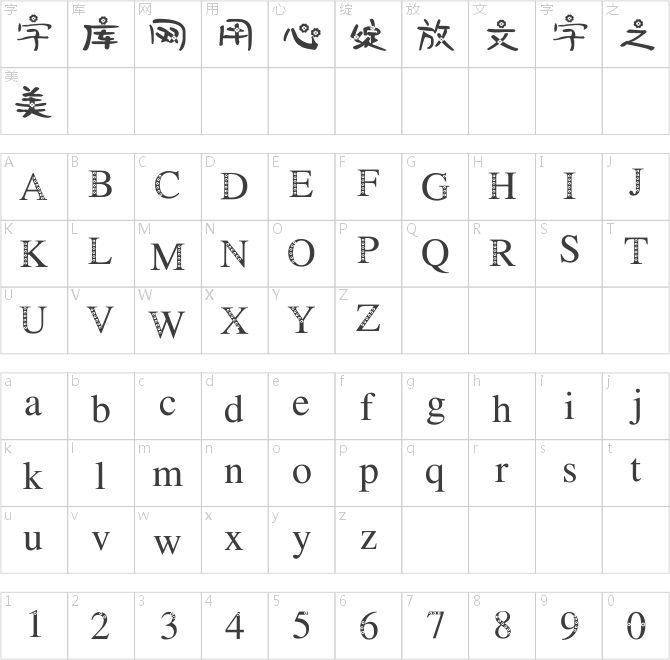
南構(gòu)花韻
南構(gòu)字庫(kù)
南構(gòu)花韻字體字庫(kù)是一款讓人賞心悅目、百看不厭的中文字體,適合各類(lèi)廣告和產(chǎn)品包裝設(shè)計(jì)應(yīng)用,字體大小3.69MB,格式為ttf字體,上傳用戶(hù)是錦程正陽(yáng),作者/版權(quán)方為南構(gòu)字庫(kù)